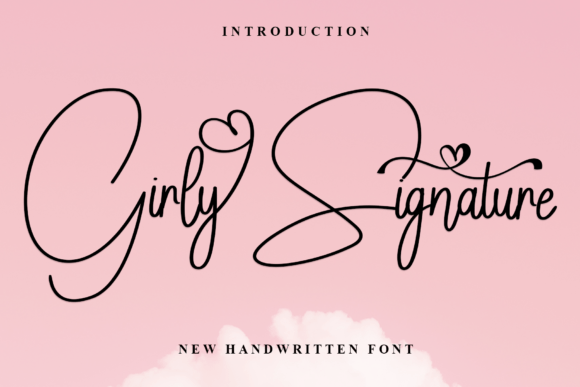
Girly Signature
Girly Signatureのような高品質の素材をお探しの場合、このプレミアムパッケージはクリエイティブなプロジェクトに素晴らしい選択です。
POD(オンデマンド印刷)製品、結婚式の招待状、またはソーシャルメディアのグラフィックを作成している場合でも、Girly Signatureは理想的です。